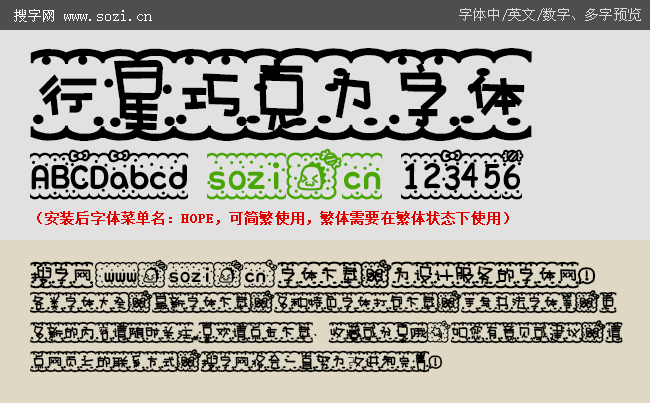
行星巧克力字體
搜字網(wǎng)給大家提供一款很可愛(ài)的手寫(xiě)風(fēng)格手機(jī)中文字體下載。修改者將它命名為行星巧克力字體,這款手機(jī)字體是在POP字體外邊加上了卡通邊框,并插入了一些可愛(ài)的卡通圖案,是一款非?蓯(ài)的兒童卡通字體,特別適合小朋友和擁有可愛(ài)童心的朋友在手機(jī)上安裝使用。